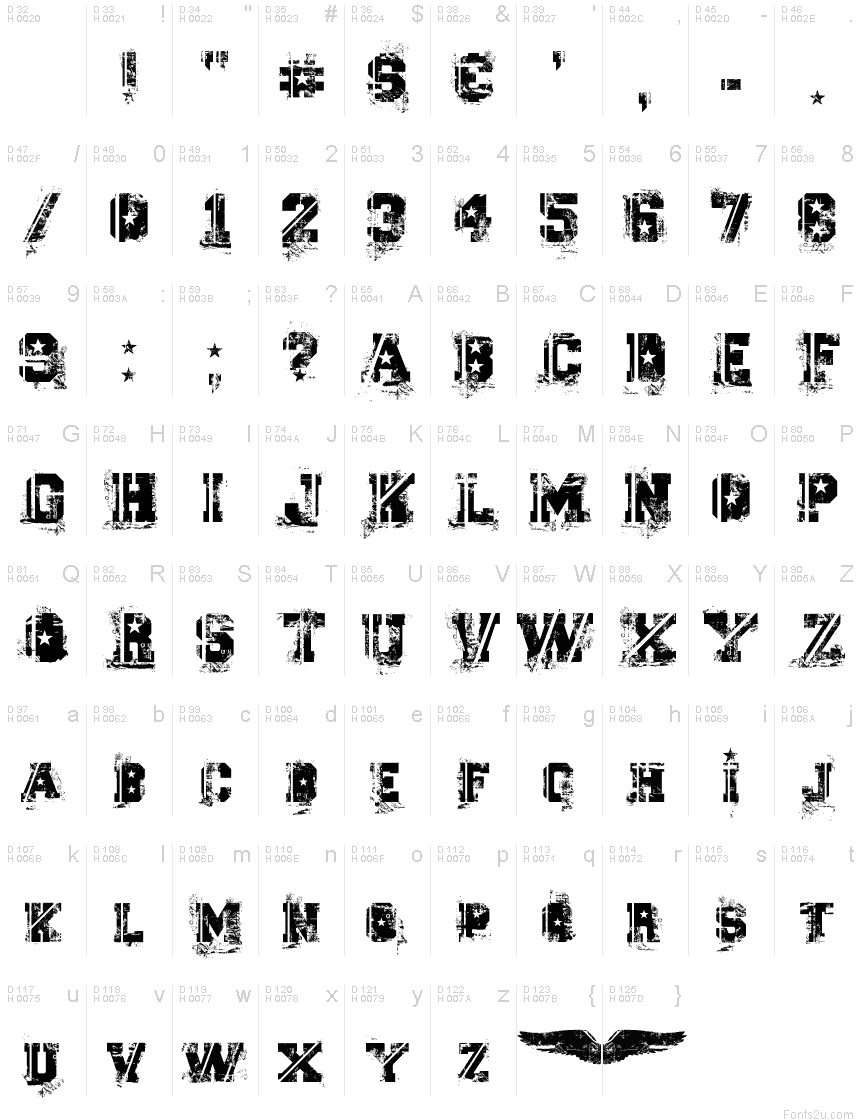
Ascent 2 Stardom od BGizzle Fonts je bezplatné grungeové display písmo s ošoupaným vzhledem připomínajícím stržené plakáty a staré pouliční značení. Velká písmena jsou hustá a bloková, narušená výraznou erozí, cákanci a drsnými mezerami; hvězda vyražená v písmenu „A“ dodává celé sadě hlasitý, městský postoj.
Hodí se na hudební letáky, skate a streetwearovou grafiku, obaly mixtapes, titulky a odvážný branding, kde font sám o sobě nese syrovou, poškozenou texturu bez nutnosti dalších efektů. Použijte jej na krátké nadpisy, logo experimenty nebo monogramy, když chcete, aby samotná písmena odvedla tu špinavou práci.